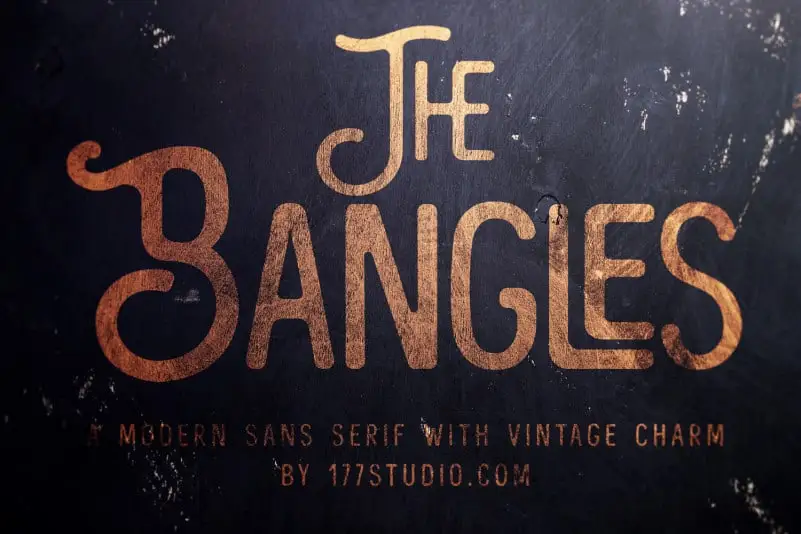
The Bangles – Vintage Font – Download Grátis
Introduzimos The Bangles Font, uma tipografia sans serif inspirada nos tempos medievais e no aristocrata. Esta coleção é uma opção incriveis para diversas aplicações gráficas, desde embalagens e cartões de visita até conteúdo criado em redes sociais. A influência medieval combina com o ar sofisticado do aristocrata para criar um visual atraente e moderno que vai bem tanto em projetos profissionais quanto em projetos pessoais. Ideal para imprimir no formato direct-to-garment em roupas, The Bangles Font é uma excelente opção para designers buscando algo único e intrigante. Este tipo de fonte não só oferece um visual atraente, mas também permite ao designer expressar criatividade e personalidade em seus projetos, tornando-o um recurso valioso para qualquer projeto gráfico. Com sua design minimalista e elegante, The Bangles Font é uma escolha perfeita tanto para quem busca algo clássico quanto para aqueles que desejam algo mais moderno e contemporâneo.